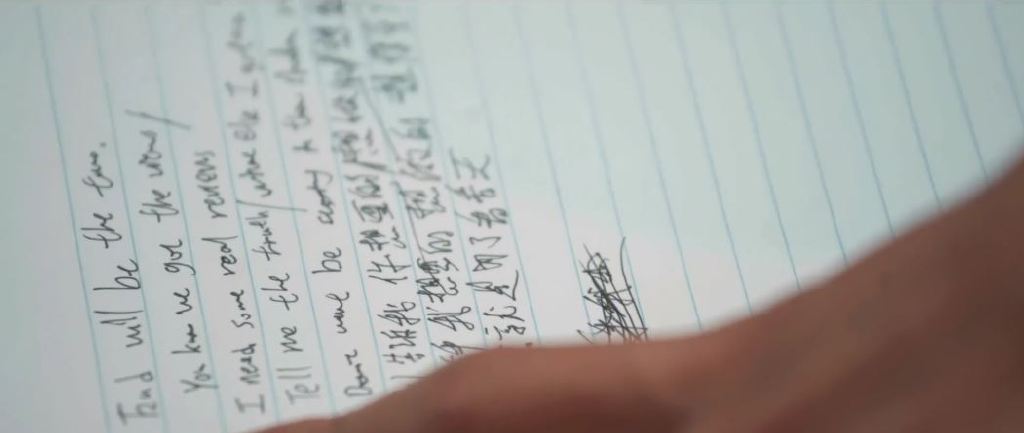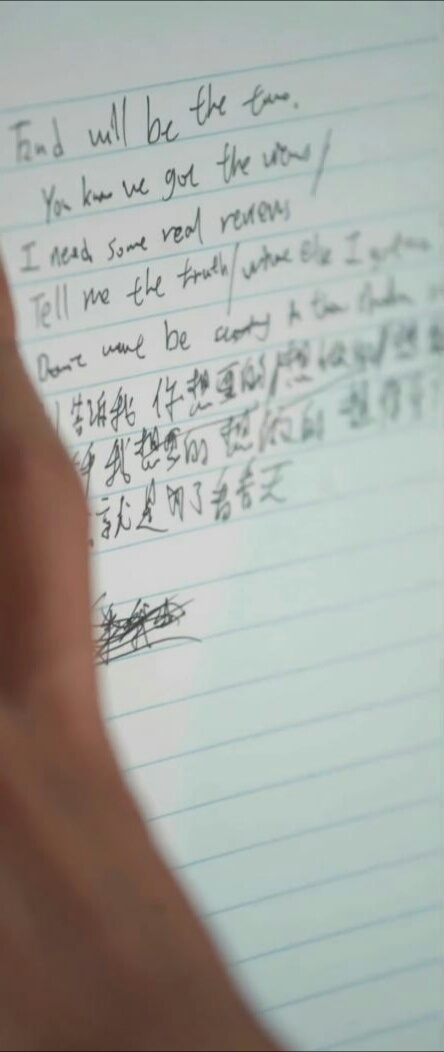
吴亦凡另类字体引爆笑 说好的字如其人呢!
爱豆分享 在6日晚公开的吴亦凡音乐纪录片《Free》第二集《回到嘻哈发源地》中,我们不仅跟随吴亦凡的讲述更深一步了解到了凡凡他眼中的嘻哈,也惊喜地发现了一位正在手写《Lullaby》最新版歌词的小盆友!但这字体....幼稚得似乎与本人高大帅气的形象完全不符啊,说好的字如其人呢!恕小编的赞美词汇匮乏~
最后还是要为我们吴梵高正名一下,像凡哥这样的高等艺术,吾等凡人怎么会懂呢?(傲娇脸)
“字体”出现在01:48左右处↓